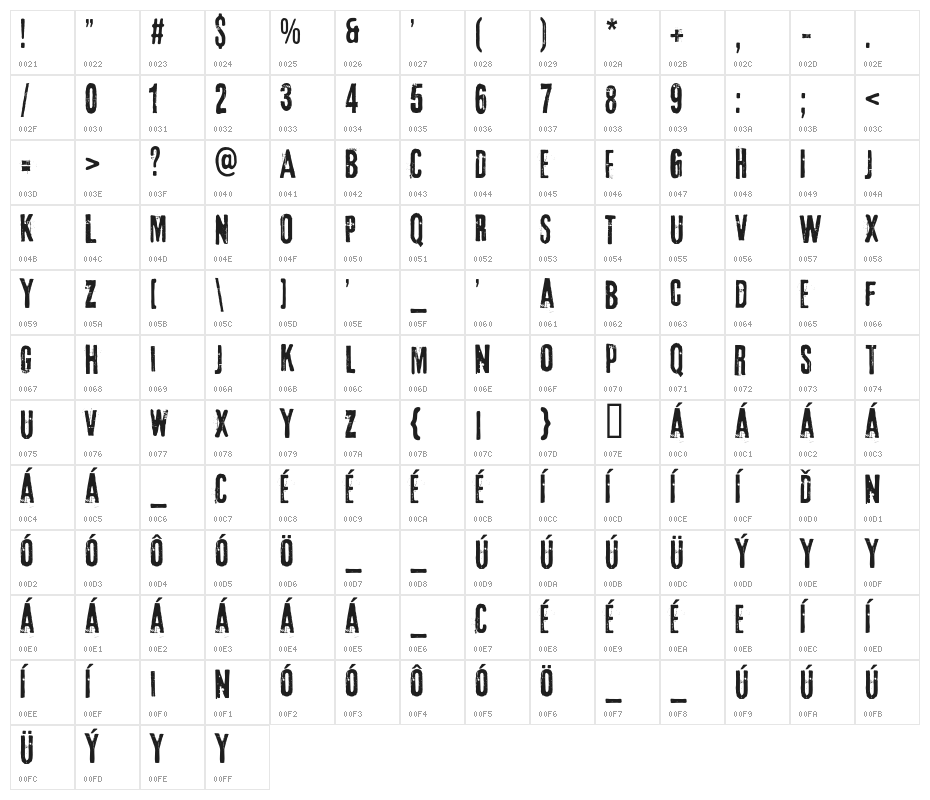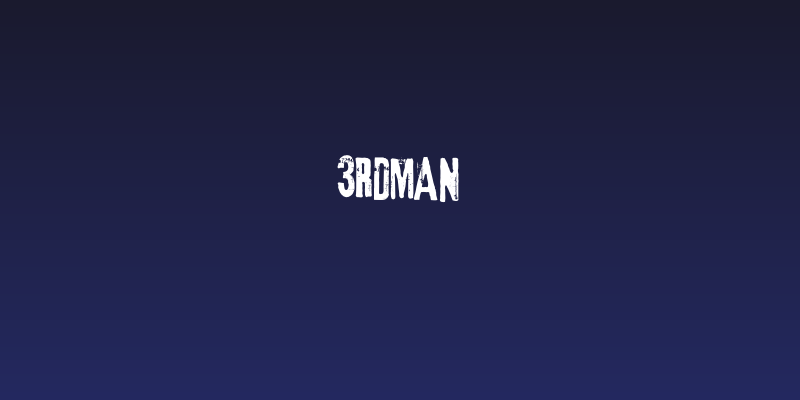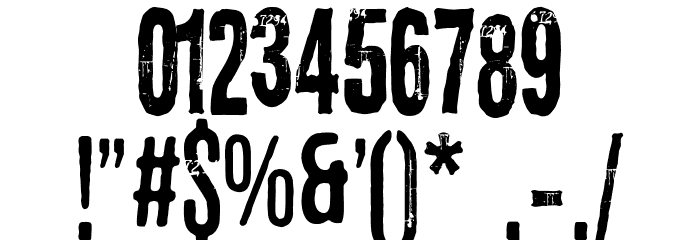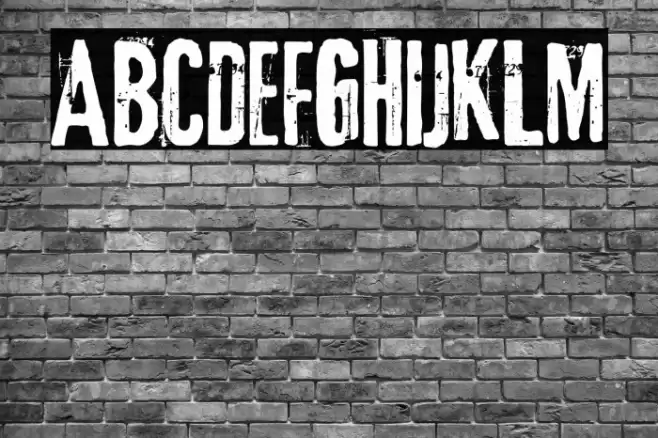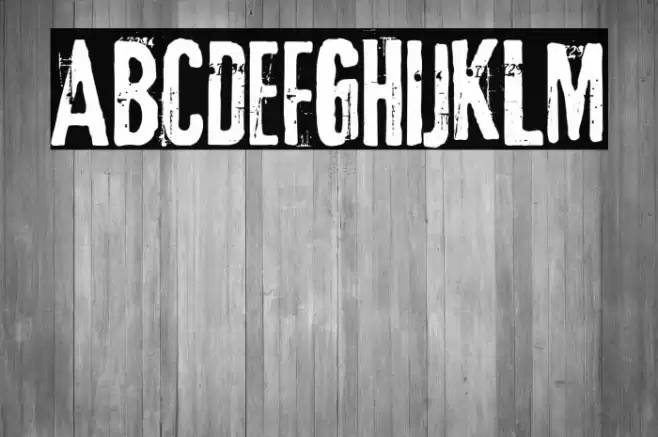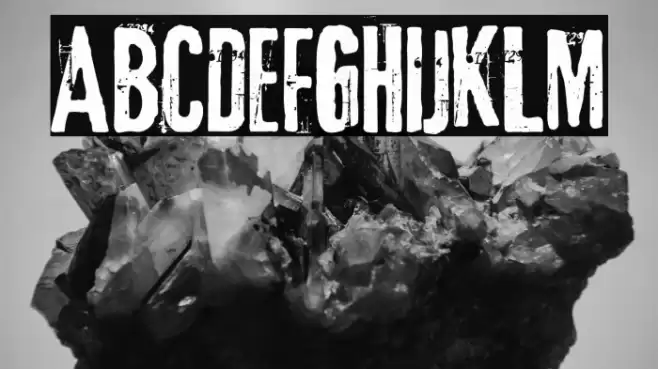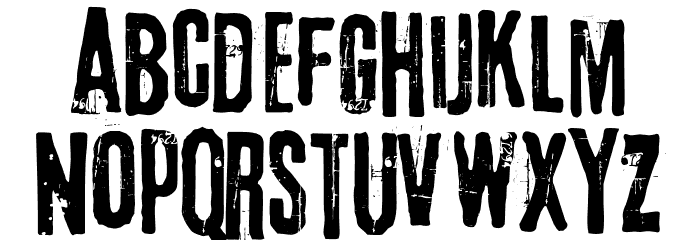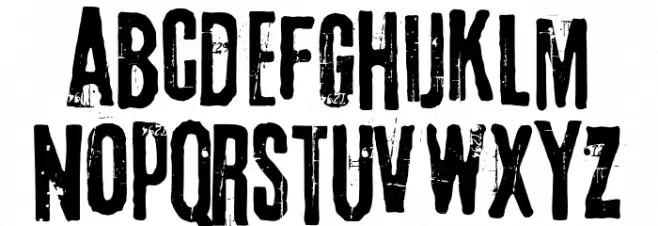
3rdMan Font
✎ Messy
| Categorías | Messy |
| Estilo general | Vintage, Grunge |
| Proyectos propuestos | Ideal for posters, album covers, branding for edgy or vintage-themed products, and any design requiring a bold, textured look. |